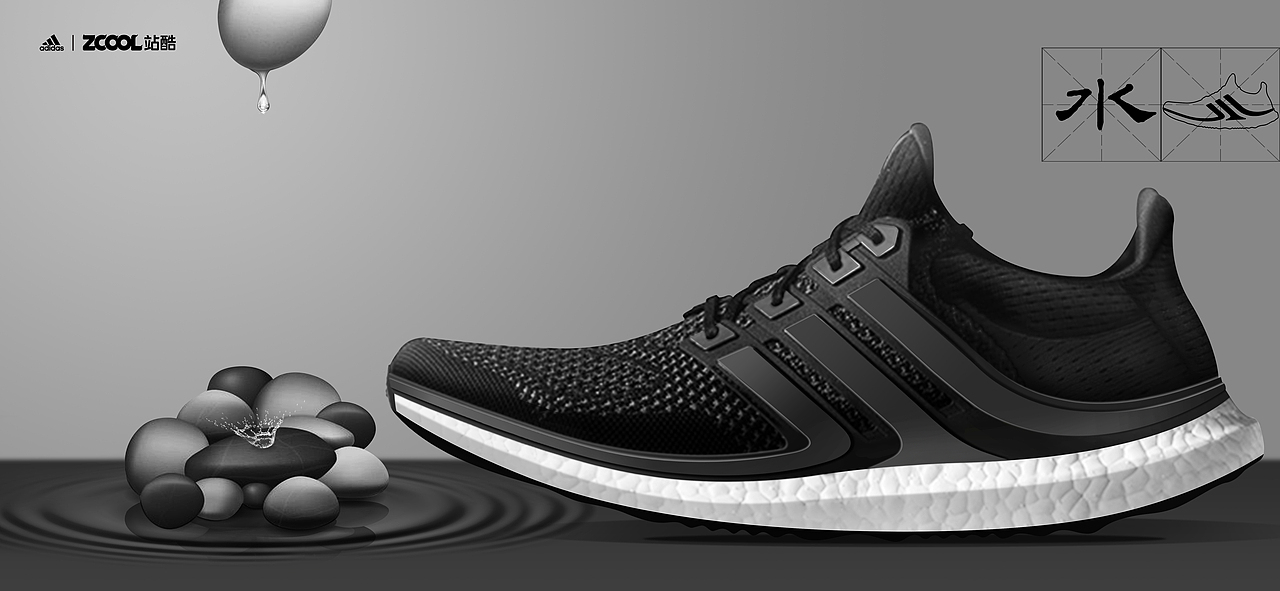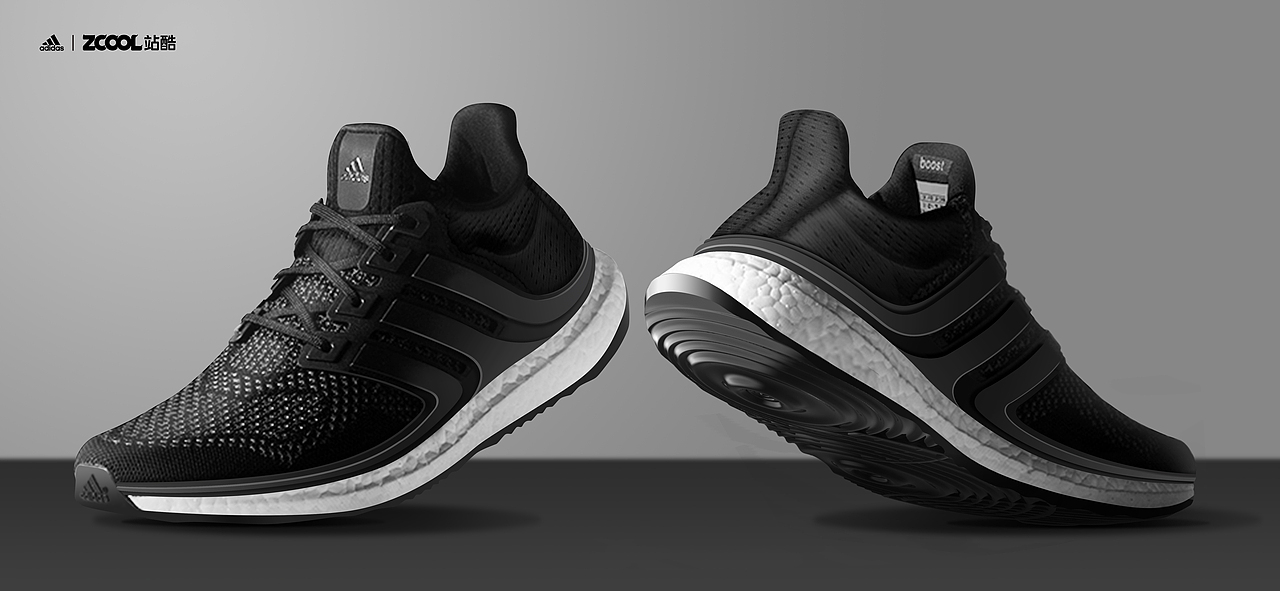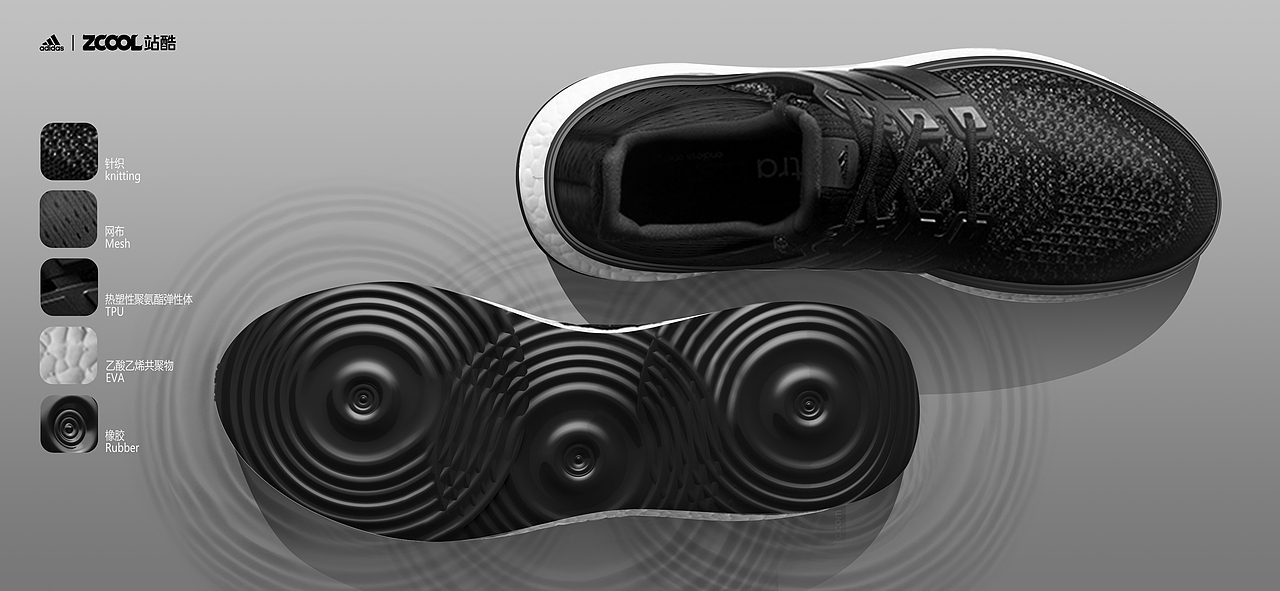
adidas Ultra Boost@水
将中国汉字“水”字融入adidas Ultra Boost跑鞋设计之中,保留adidas Ultra Boost跑鞋经典部分和“水”字保持辨认度下形变与侧面贴面融合,搭载原有招牌石纹Boost中底,大底设计成水纹涟漪与贴面“水”字相呼应,整体设计表达“水滴石穿”坚持不懈运动精神。
“水”字在中国文化中代表人的精神、境界与追求,在我们的生活当中,“水”以其深厚的文化底蕴滋润的着人们的心灵,对“水”的认识和感悟,能使我们豁然开朗、心旷神怡:
“水利万物而不争”最高的德性、最高的善就像水一样,具有道的精神;
“湖光秋月两相和,潭面无风镜未磨”的平静安稳;
“泉眼无声惜细流,树阴照水爱晴柔”的和谐美好;
“水滴石穿”的坚持不懈......